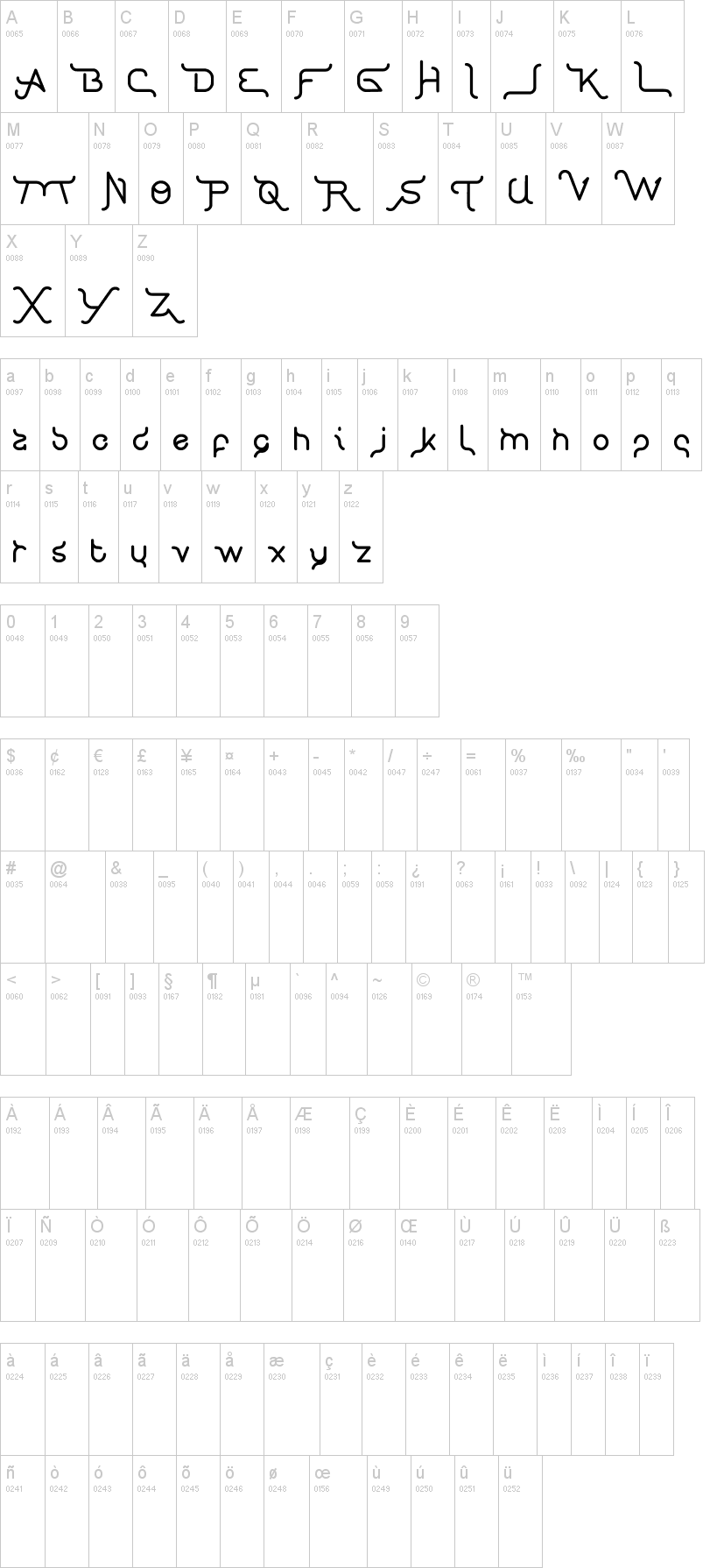
和排版王 King Of Font And Typography 是一款专业的字体和排版工具,可以帮助用户轻松实现字体和排版的设计。它拥有一个智能的字体和排版工具,可以让用户简单快捷地设计出他们想要的字体和排版,并且还可以在短时间内提供定制的字体和排版设计服务。此外,它还提供一系列的字体管理工具,可以帮助用户管理和更新他们的字体库,让他们可以轻松找到所需的字体,从而节省时间和精力。内容介绍
King Of Font And Typography是一款非常不错的手写艺术字体,具有很好的视觉感,适合于文化类的宣传设计、商业类品牌的广告和产品包装设计以及个性化文字排版等较多场景。